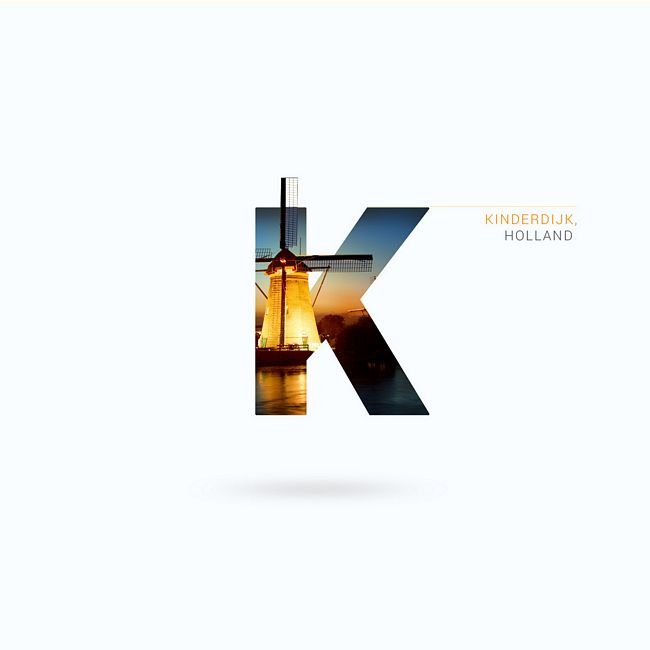
Viajar e conhecer novos lugares é algo que muitos fazem com imenso prazer. Seja de carro, de moto, a pé ou de avião, é possível sair e se deparar com novas culturas.
Mas, além desses meios de transporte, acrescenta-se mais um: a tipografia.
No projeto “Around the world with type” os estudantes de design gráfico Rigved Sathe e Payal Jagwani nos convidam para uma linda viagem tipográfica para diversos lugares.
Passando por todas as letras do alfabeto, os futuros designers exploram cada localidade de modo incrível.